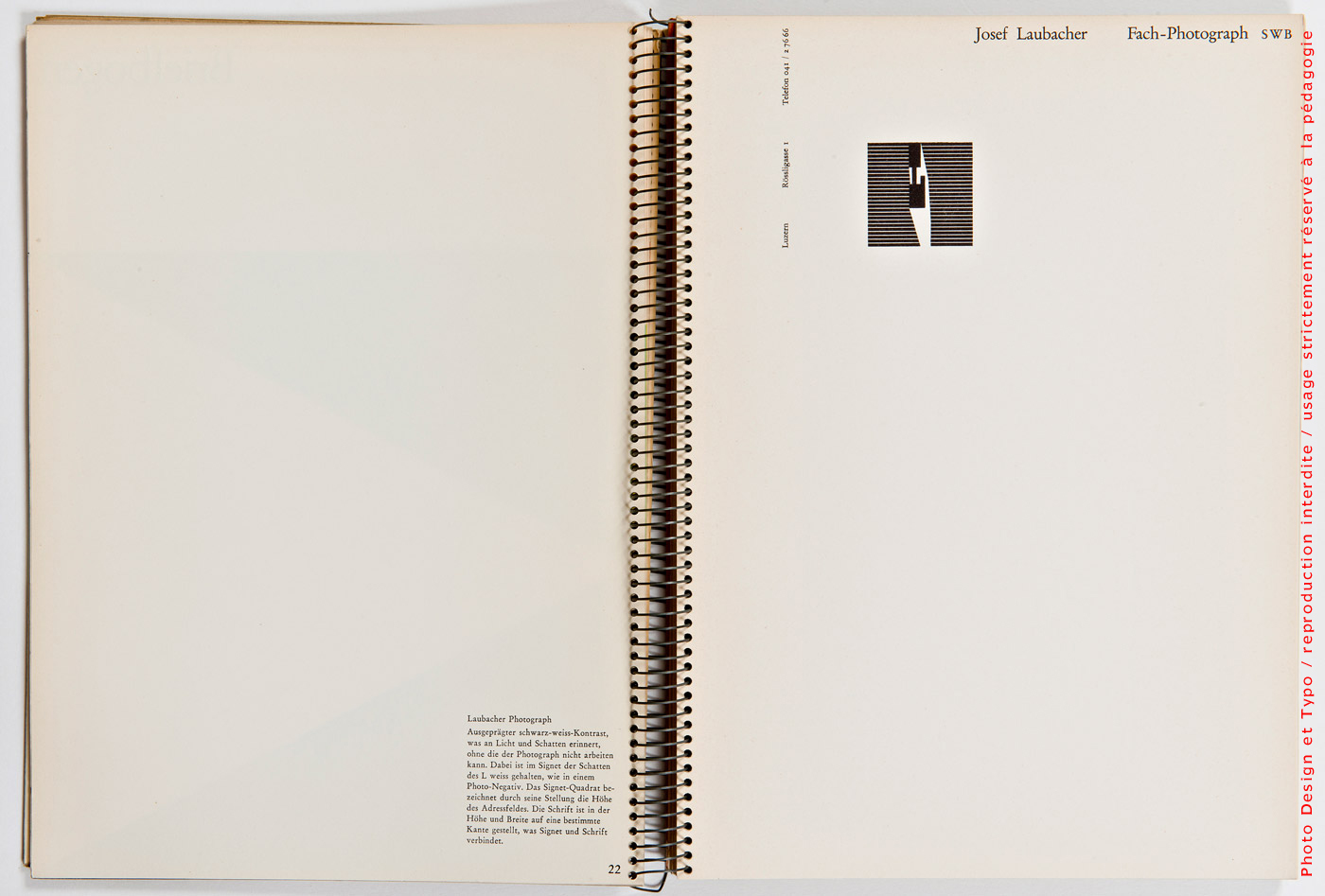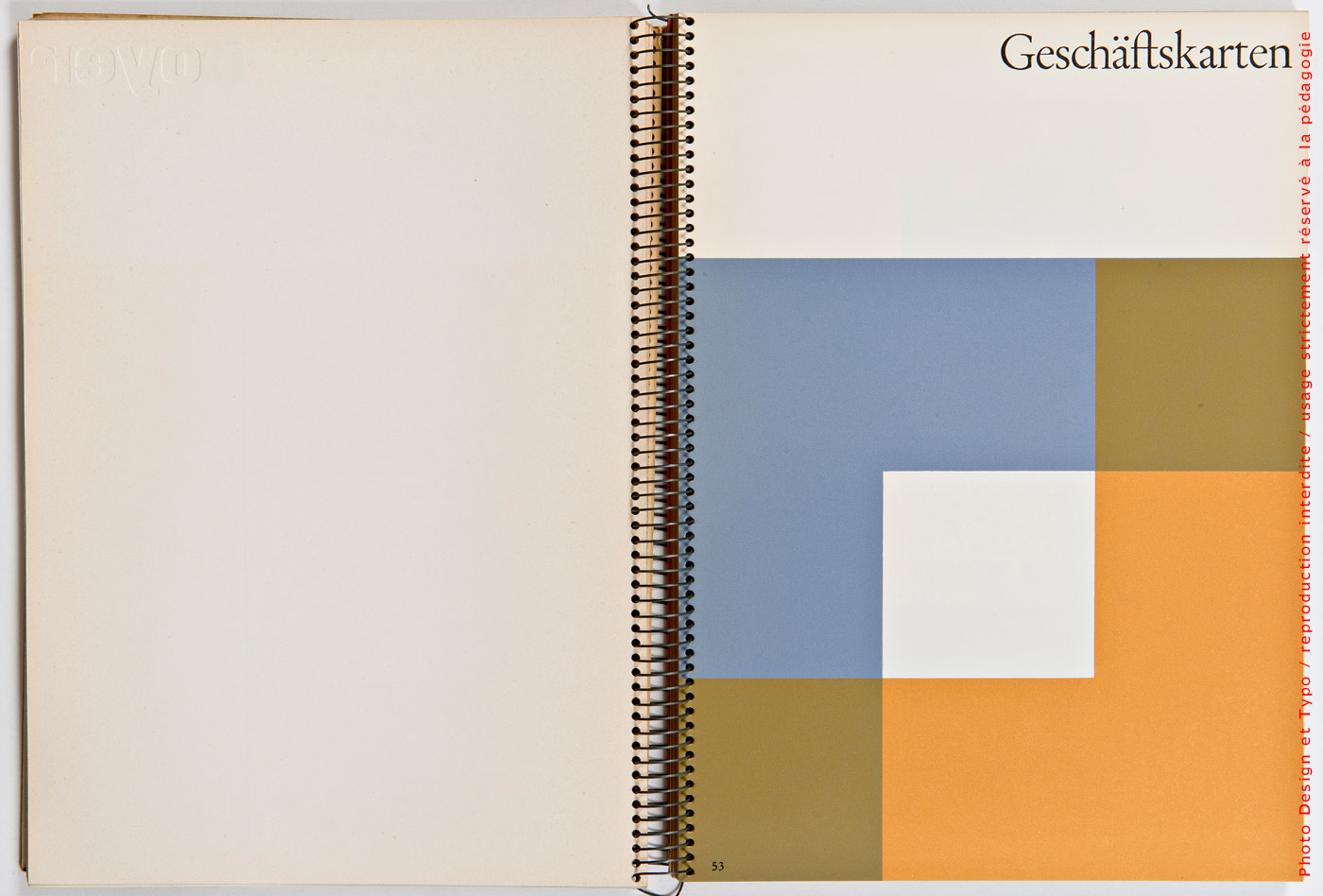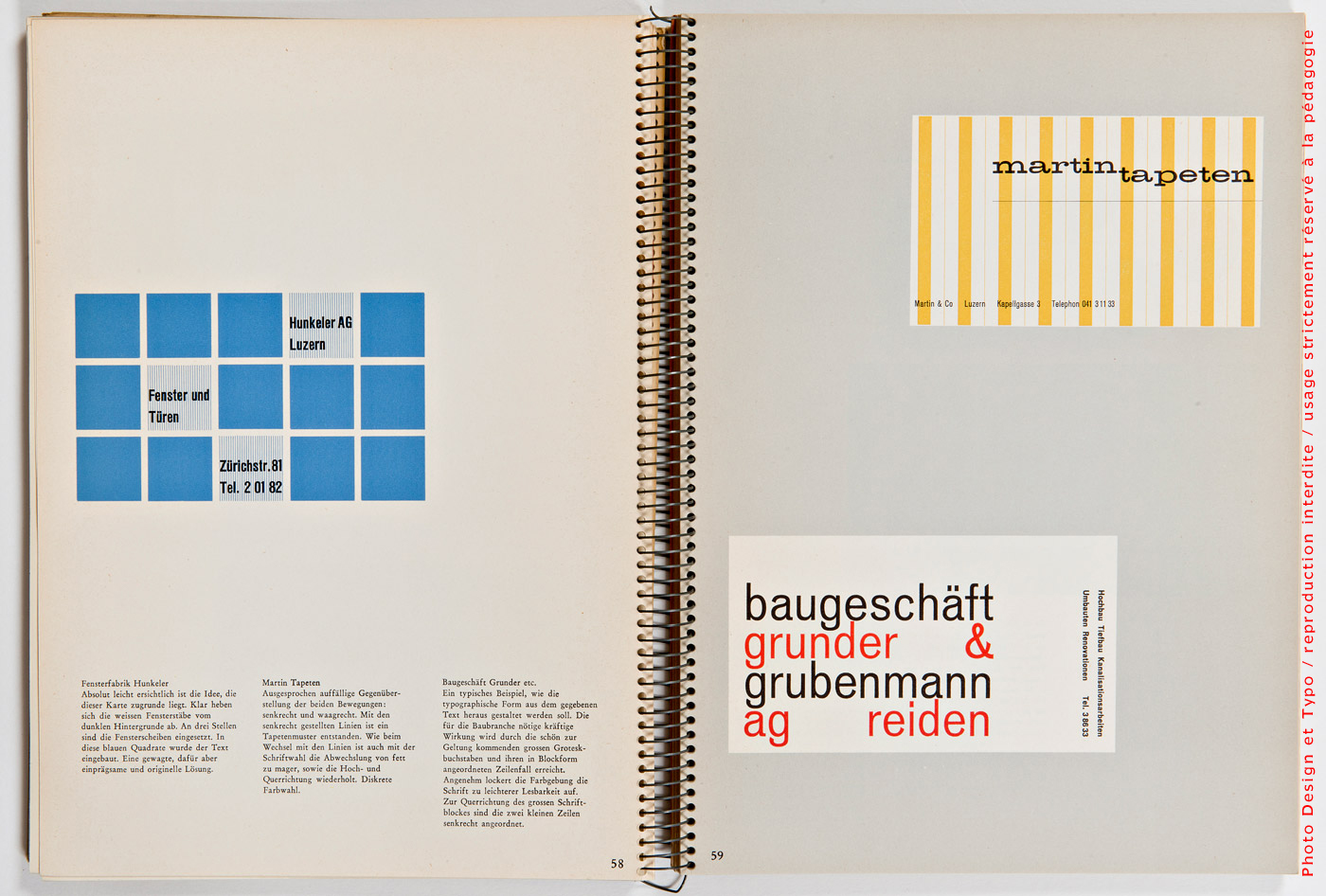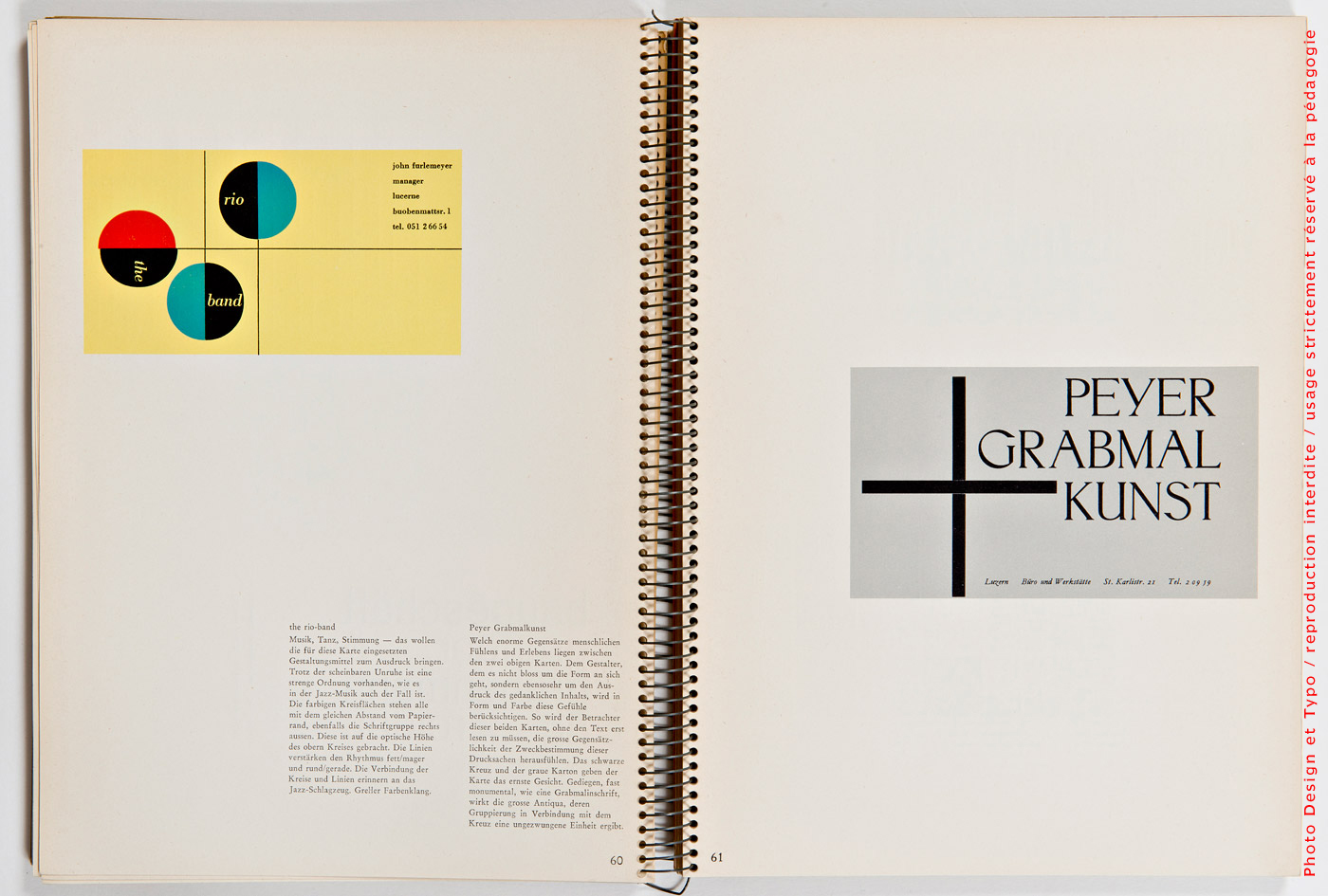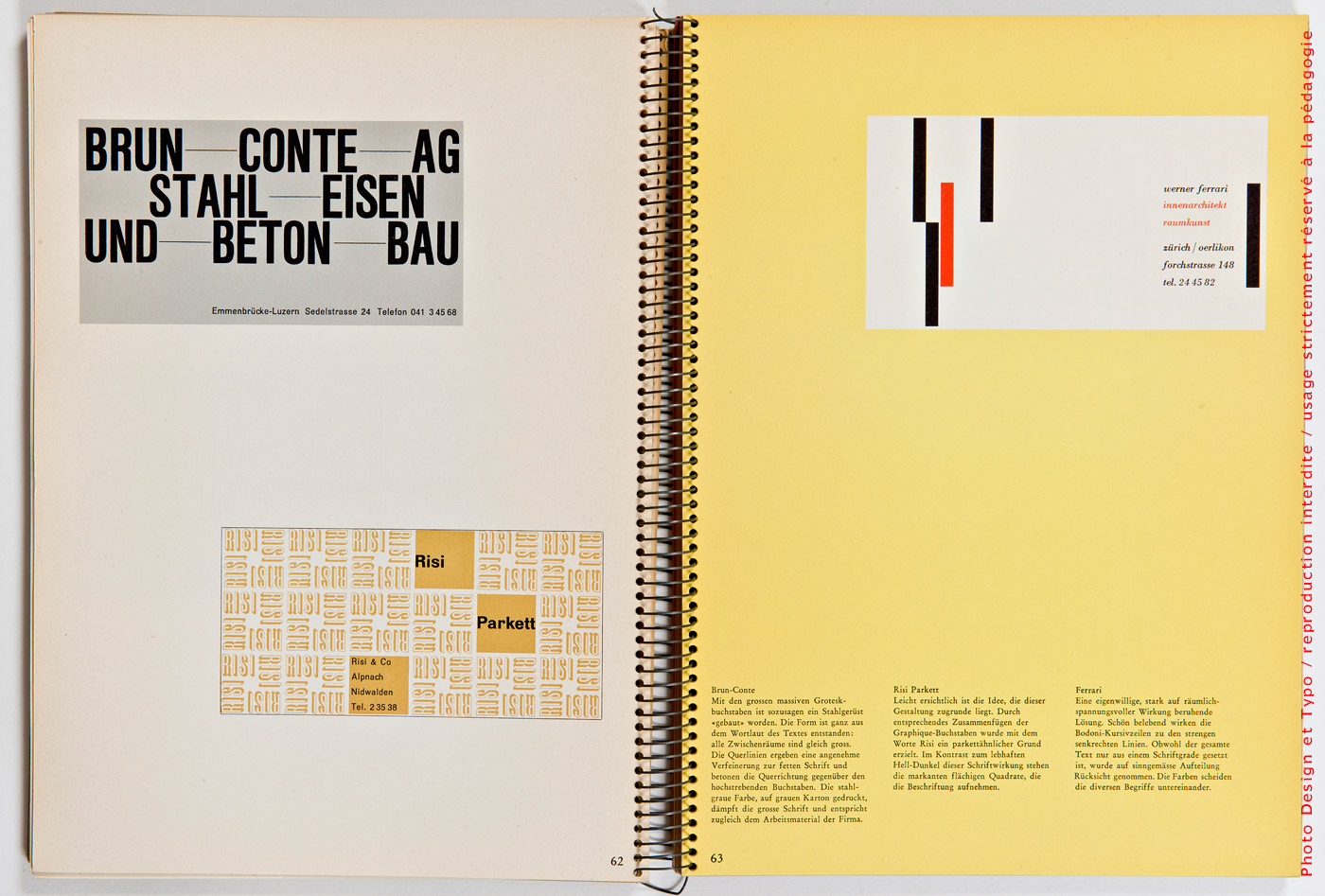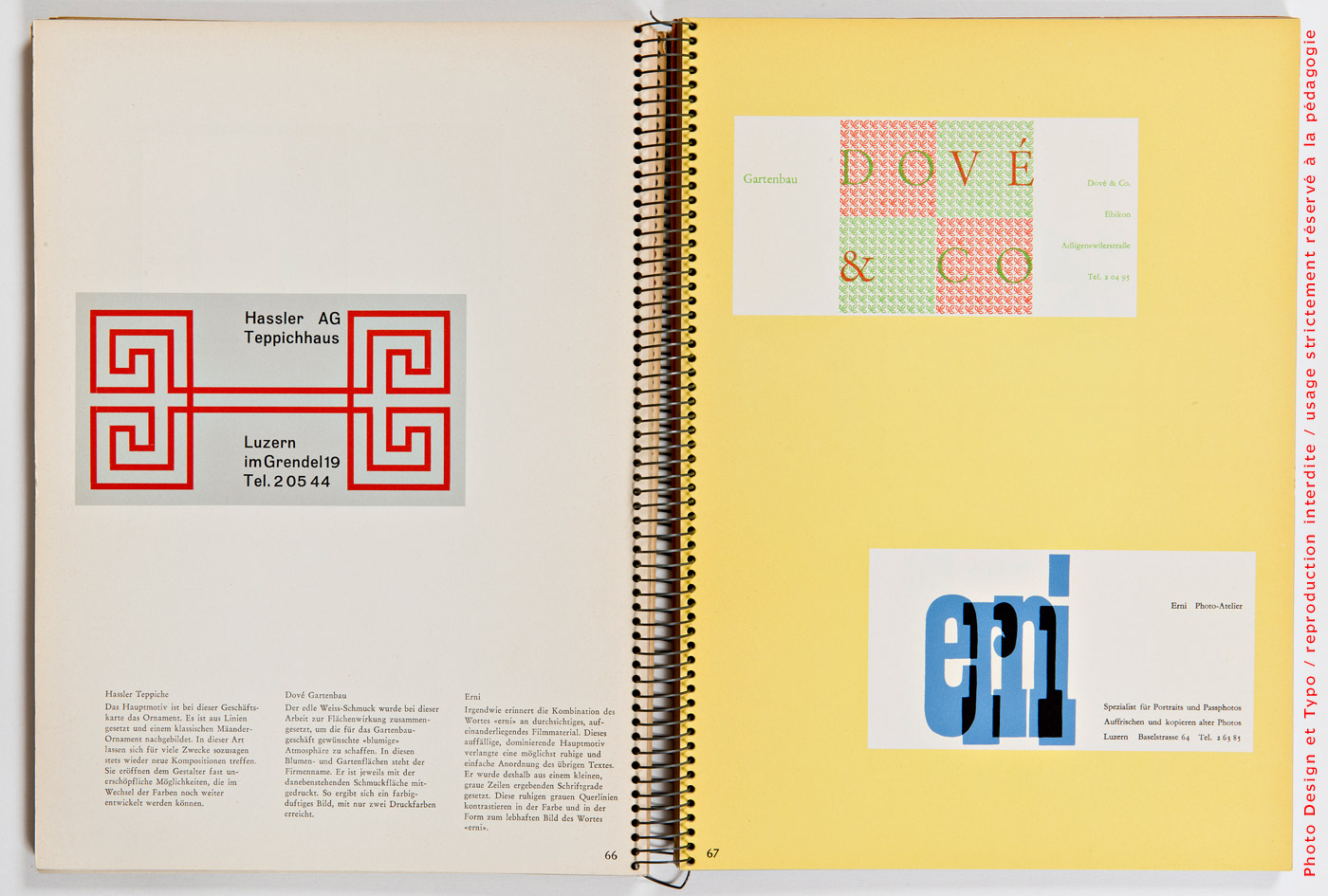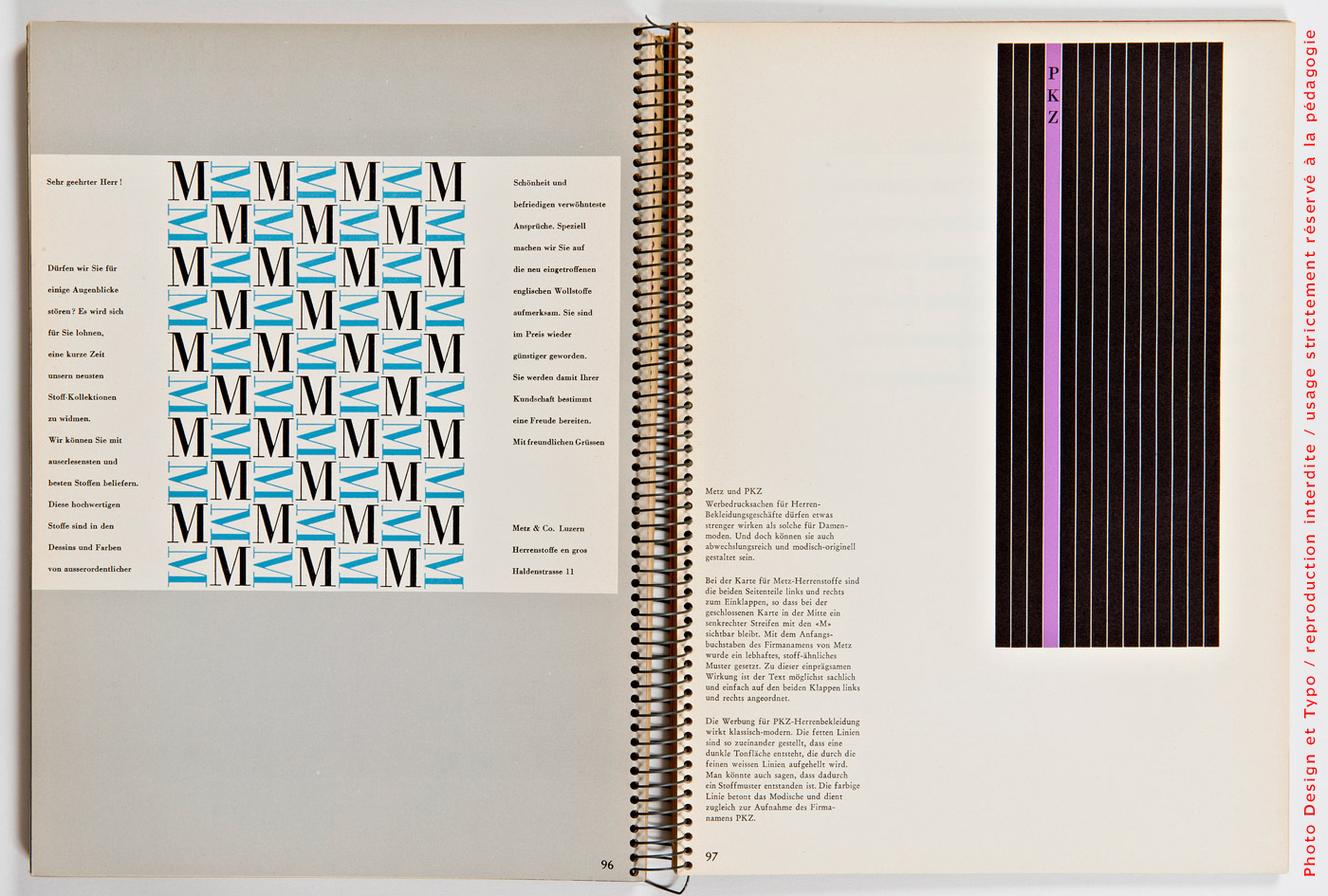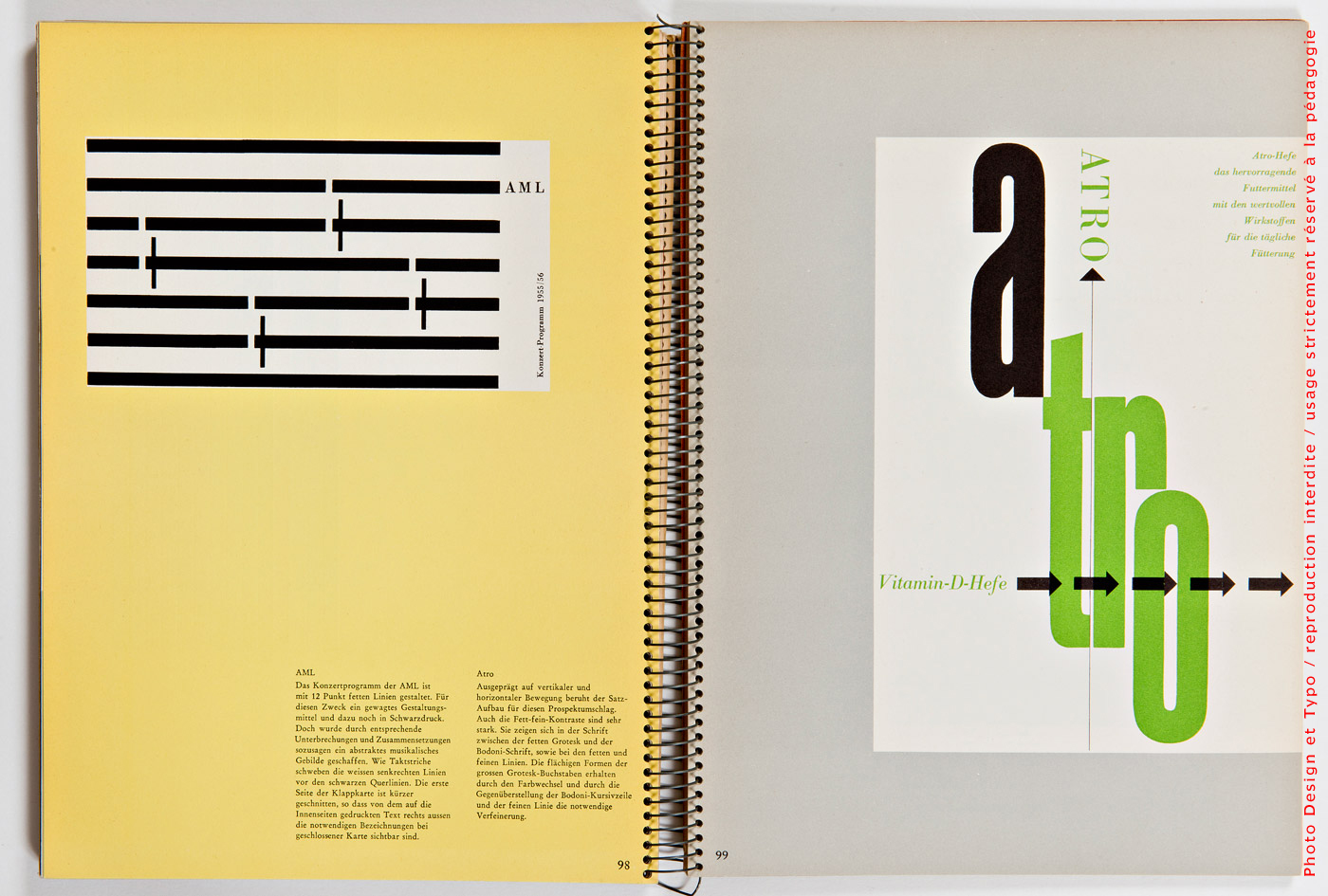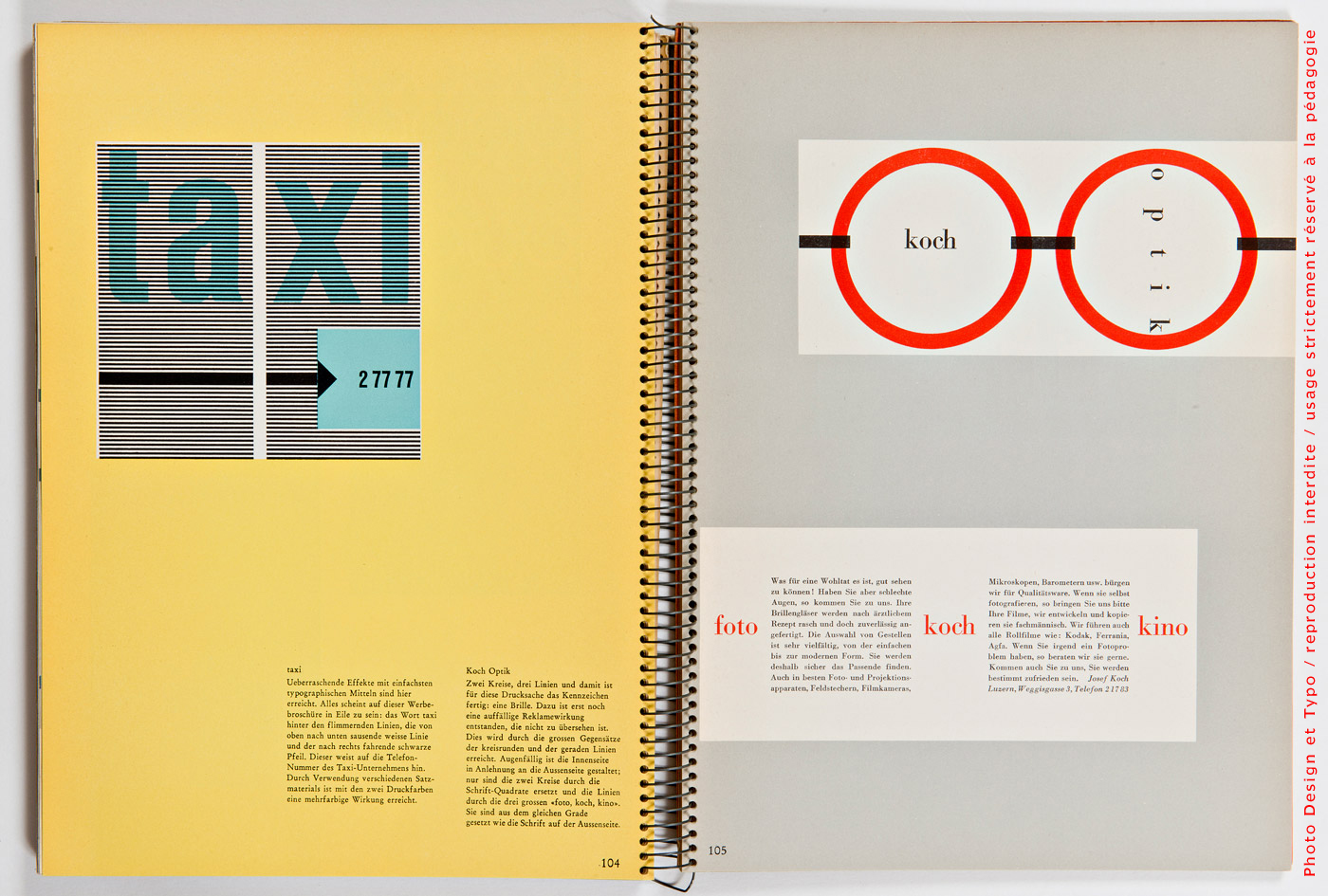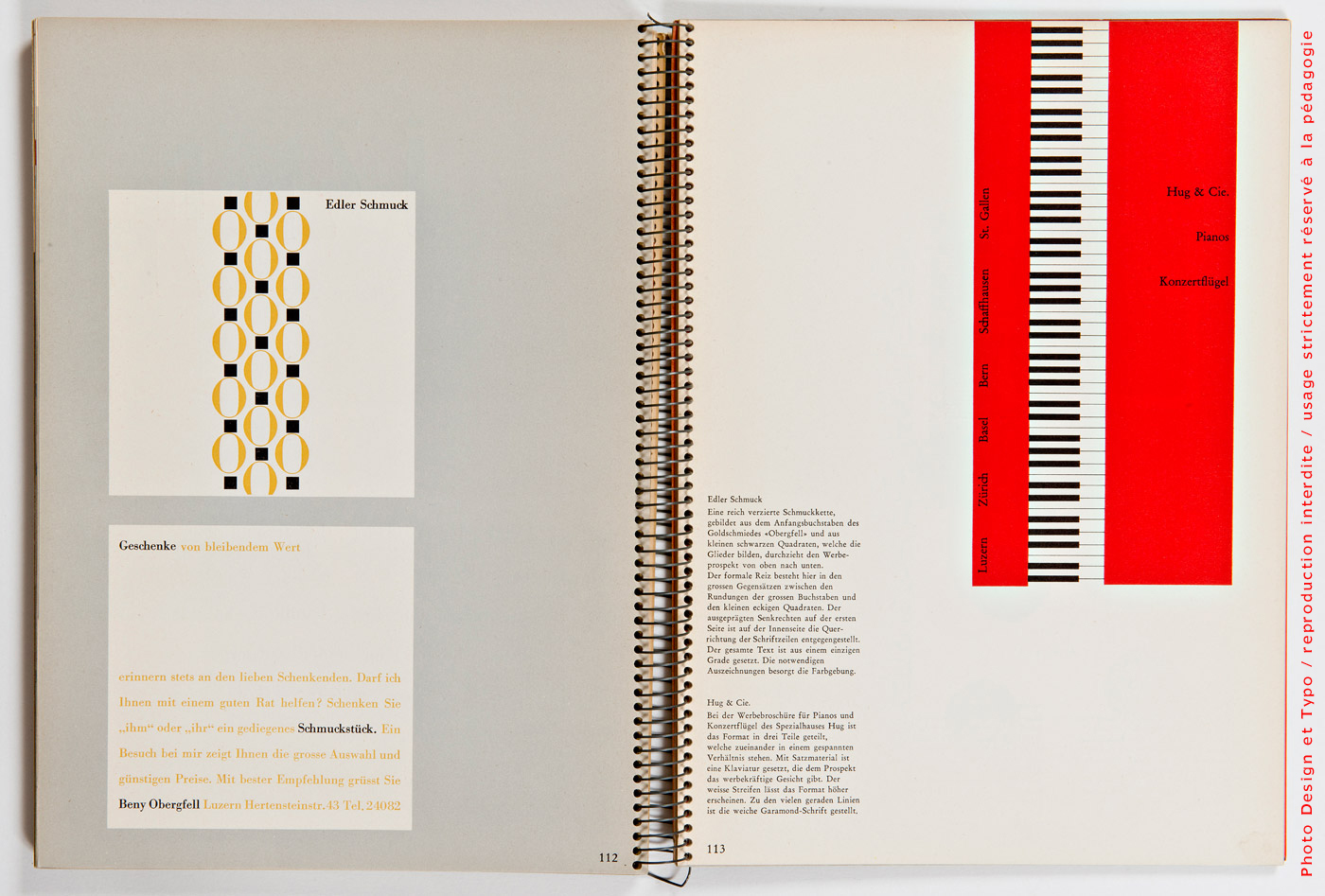
Hommage à la Typographie Suisse | un album de Walter Marti | 1957
Cet album témoigne de la versatilité des moyens typographiques pour créer, logos, identités visuelles, chartes graphiques et éditions. En somme nous sommes en face d’un véritable langage graphique aux ressources infinies, où l’on voit que la lettre devient image à l’instar de ce qu’écrivait Massin dans ses ouvrages. Grande tradition suisse de même. Publié à Lucerne en Suisse en 1957, nous sommes bien après la guerre. Dans les années 50. Le monde vit la reconstruction et ces exemples de lettrages témoignent de ce désir d’architecturer l’espace, d’en faire un lieu construit à la Bauhaus. On peut regretter bien sûr que les Suisses aient peu emprunté au constructivisme Soviétique, bien qu’ayant été parmi les plus fervents promoteurs du mouvement DaDa, mais il n’en demeure pas moins qu’ils ont été largement en avance sur le reste de l’Europe. À l’exception peut-être de l’Allemagne pour les raisons que l’on connait, et l’Angleterre qui a toujours accordé une importance capitale à la calligraphie et à l’identité visuelle. Bien entendu je n’oublie pas les apports graphiques des néerlandais ni des italiens… mais voilà, il faut bien toujours qu’il y ait une première fois :) //peter gabor